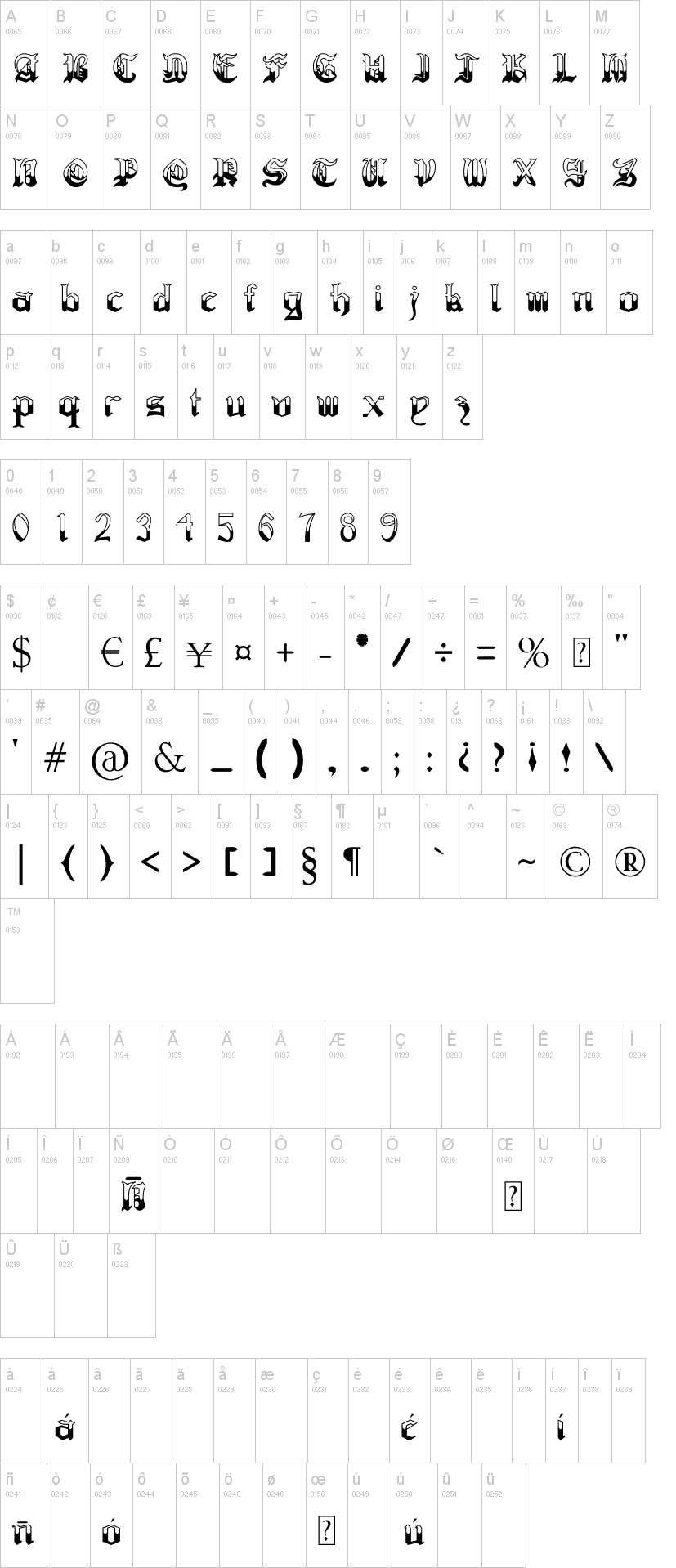
Regothic
Regothic 是一种经典的古典风格的字体,具有英国传统的古典风格。它具有宽松的字形,较大的字符间距,以及明显的竖直线条和曲线。它通常用于书籍,杂志,标题,标签,海报,海报等。它可以提供一种传统的外观,并且可以在各种大小的文本中使用。
Regothic是一款非常不错的手写艺术字体,具有很好的视觉感,适合于文化类的宣传设计、商业类品牌的广告和产品包装设计以及个性化文字排版等较多场景。